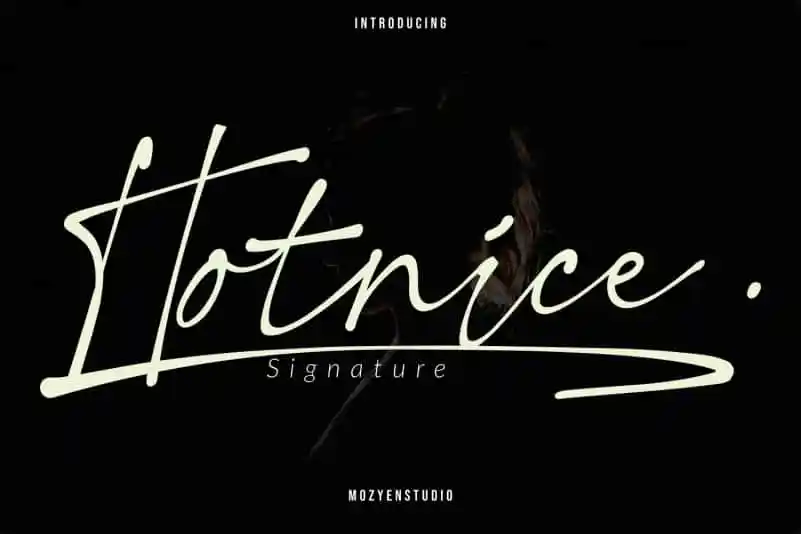
Hot Nice Handwritten Font – Download Grátis
Hot Nice Handwritten Font é uma fonte script elegante e única ideal para qualquer projeto criativo. Com seu estilo chic e sofisticado, essa fonte foi projetada por Mozyen Studio para adicionar um toque atraente aos seus designs. “Hotnice” pode ser usada em uma variedade de aplicativos, como design de casamentos, criação de frases lindas para t-shirts, cartões de negócios e até mesmo logomarcas e campanhas promocionais. Com seu charme único e suas linhas fluidas, “Hotnice” Signature Font é a escolha perfeita para aqueles que desejam um toque sofisticado em seus projetos. O design elegante da fonte vai ao encontro do estilo minimalista ou mais artístico de qualquer projeto. Seja para criar uma identidade visual única ou complementar um design já existente, essa fonte certamente deixará seu trabalho ainda mais atraente e especial.